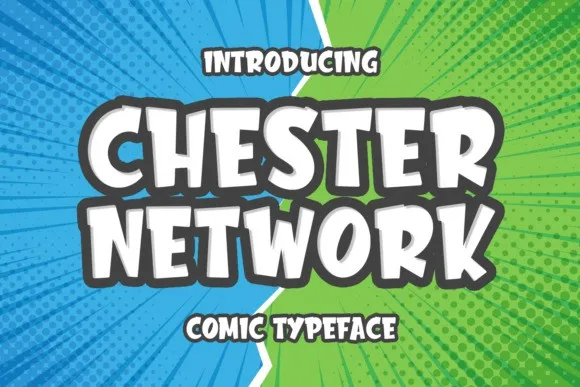
Introduzo-vos Chester Network – uma tipografia sem serif que transmite a energia e a alegria de uma história de fábulas. Desenvolvida pelo designer f0rdesigner, esta fonte é ideal para quem busca um visual vibrante e encantador, perfeito para incorporar em diversas áreas, desde o logotipo até às peças de moda. Uma das características mais notáveis do Chester Network é a sua aparência robusta e espelhada nos selos dos livros best-sellers. Esta fonte, além de ser facilmente identificável, também é versátil o suficiente para se adaptar ao design de capas de livros e até mesmo ao cartaz da indústria cinematográfica. Chester Network oferece um toque único que faz com que a sua utilização seja não apenas funcional, mas também uma forma elegante de expressão. Ideal tanto para aplicações gráficas como o logotipo de marcas, embalagens e rótulos, até mesmo para as camisetas, Chester Network é perfeita para usar em qualquer elemento visual que deseja destacar. Se procura uma fonte que combine a simplicidade do sans serif com um toque vibrante e criativo da linguagem de quadrinhos, o Chester Network é definitivamente a escolha certa. Não hesite em dar-lhe uma oportunidade para explorar as possibilidades incríveis desta tipografia única.